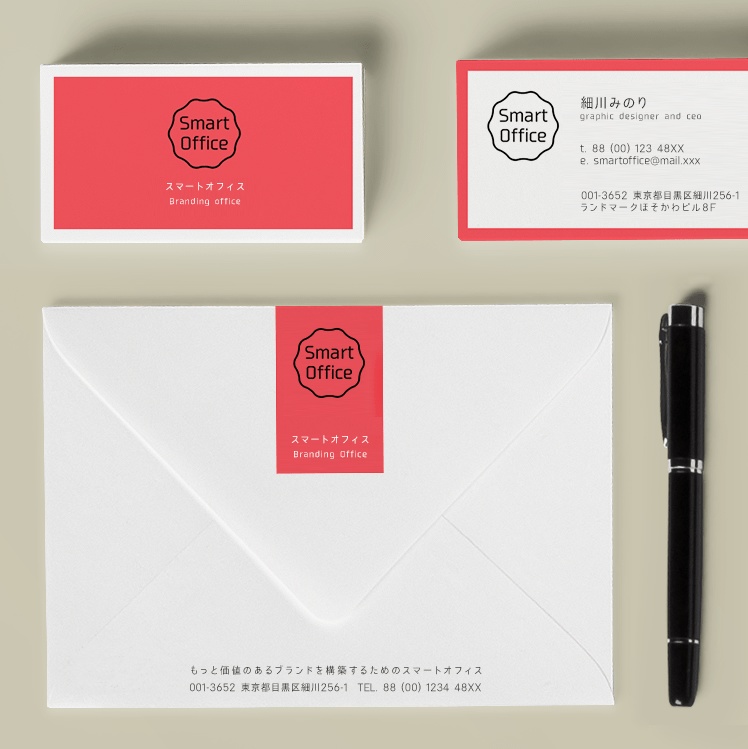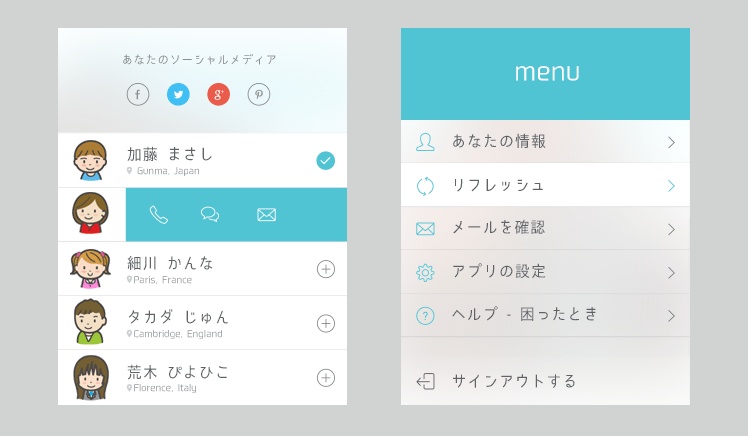
スマートフォントUI
スマートフォント フリーフォントのスマートフォントUIは、無料ダウンロードでき商用可能なおしゃれでかっこいい日本語書体。このフリーフォントは第二水準の漢字も含まれ、エクセル、ワード、Adobeイラストレーター等のアプリケーションで自由に加工して使えるゴシック体です。ひらがな、カタカナ、アルファベット、数字の字体をオリジナルで制作し、漢字をIPAexゴシックを改良したフォントで補完しています。 フォントのデザイン特徴について スマートなデザインを実現するために約90%のコンデンスド(長体、つまり縦長)になっています。グリッド(方眼)を意識したシステマチックなデザインで横組み、縦組みでのスッキリとしたモダンな表現を可能にします。また漢字に対して仮名文字がこぶりなフォントデザインになっているのも特徴です。モダンゴシック体(新ゴ[モリサワ]、ロダン[フォントワークス]等)で多く見られる、フトコロの広い骨格ではなく、クラシックな落ち着いた骨格なので幅広い用途で活躍します。グラフィックデザイン、広告などの用途はもちろんですが、ウェブ(webフォント)やアプリなどのスクリーン・デバイス上での見栄え・UI等での読みやすさを重視してデザインされています。タイトル・見出しなど大きなサイズでは、格好良さとおしゃれな雰囲気を表現でき、小さなフォントサイズでは読みやすさを感じられるように、文字のデザインをシンプルにする・濁点の間隔を広めにするなどの工夫がされています。 通常のフォントファイル(日本語等幅)以外にプロポーショナルフォントを同梱しています。プロポーショナルフォントとは、文字毎に文字幅が異なるフォントのことです。プロポーショナルフォントについては横組み専用になります。プロポーショナルでは約20%以上の多い文字数を同じスペースで記載することが可能です。 オープンソースのフォントのライセンスについて このフォントをご使用になるには、解凍したダウンロードファイルに含まれる「IPAフォントライセンス」の内容を読みください。 フォントは以下のライセンスに準じます。フォント同梱のテキストをお読み下さい。 * IPAフォント (IPA_Font_License_Agreement_v1.0.txt) ■フォントの商用利用・再配布・プログラムへの埋め込みについて 作成した印刷物およびデジタルコンテンツ・ソフトウェアにつき、その商用・非商用・フリーウェアに関わらず放送、通信、各種記録メディアなどの媒体の形式も問わず、自由に使用をする事が可能です。ただし、これはIPAフォントのライセンスの元にあり、IPAフォントライセンスを必ずご覧下さい。 ウェブフォント・アプリ・プログラムに埋め込む場合に制限があります。以下のサイトをお読み下さい。 https://www.flopdesign.com/freefont/smartfont.html ⚠️このフォントは自由に動画に使えるフォントです。ご利用の際は次のクレジットを入れていただけると、ものすごーく喜びます! –––––––––––––––––––––––––––––– フォント:スマートフォントUI フリーダウンロード:https://flopdesign.booth.pm/items/2296502 –––––––––––––––––––––––––––––– フォローしてください。 X ▶ https://twitter.com/flopdesign Instagram ▶ https://www.instagram.com/flopdesign.font Threads ▶ https://www.threads.net/@flopdesign.font